行書体・楷書体・ポップ体
行書体(ぎょうしょたい)と楷書体(かいしょたい)は筆文字の行書と楷書を基にデザインされた書体です。ポップ体(ぽっぷたい)は広告や商品のPOPなどに使われる書体で手書きの雰囲気も残しています。
行書体・楷書体・ポップ体一覧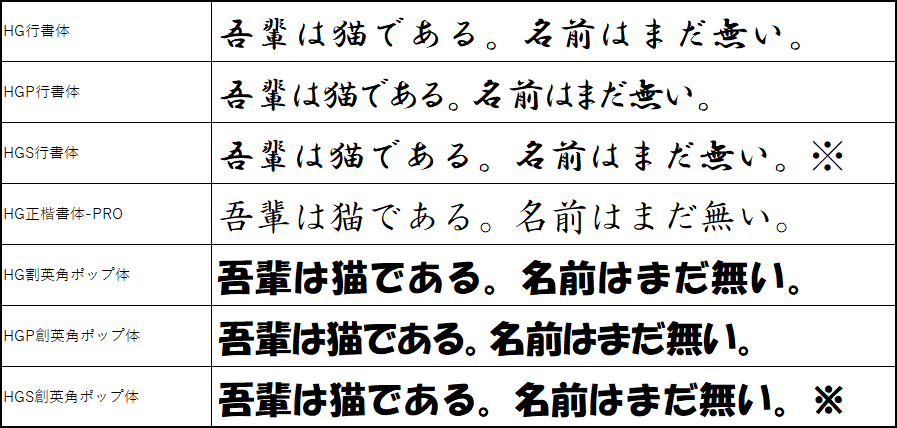
※=半角文字だけプロポーショナルフォント。
行書体
HG行書体(等幅フォント)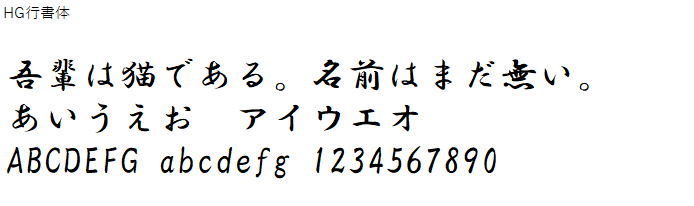
HGP行書体(プロポーショナルフォント)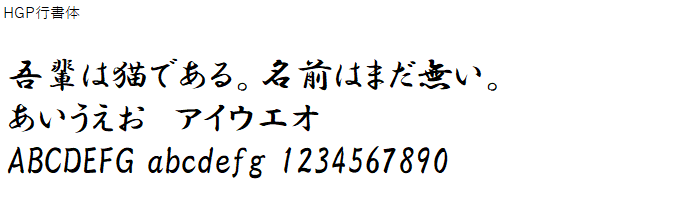
HGS行書体※半角文字だけプロポーショナルフォント。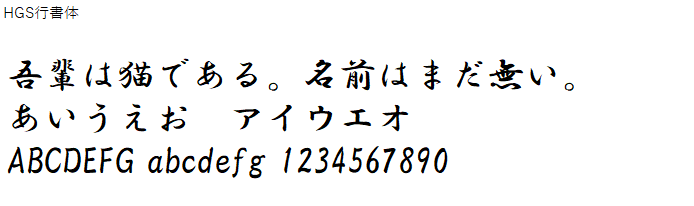
楷書体
HG正楷書体-PRO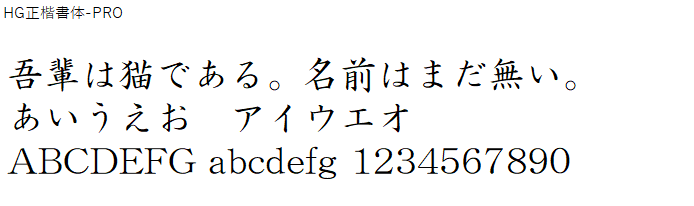
ポップ体
HG割英角ポップ体(等幅フォント)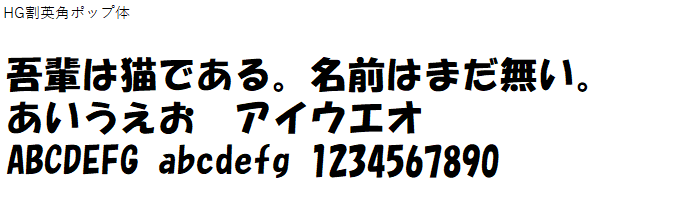
HGP創英角ポップ体(プロポーショナルフォント)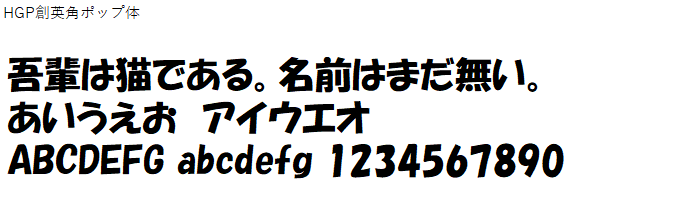
HGS創英角ポップ体※半角文字だけプロポーショナルフォント。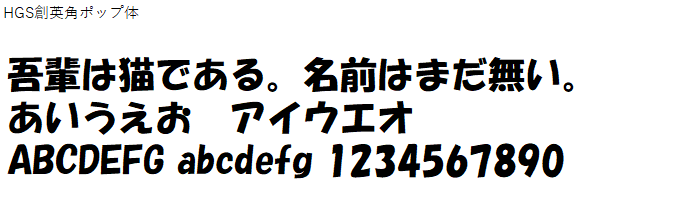